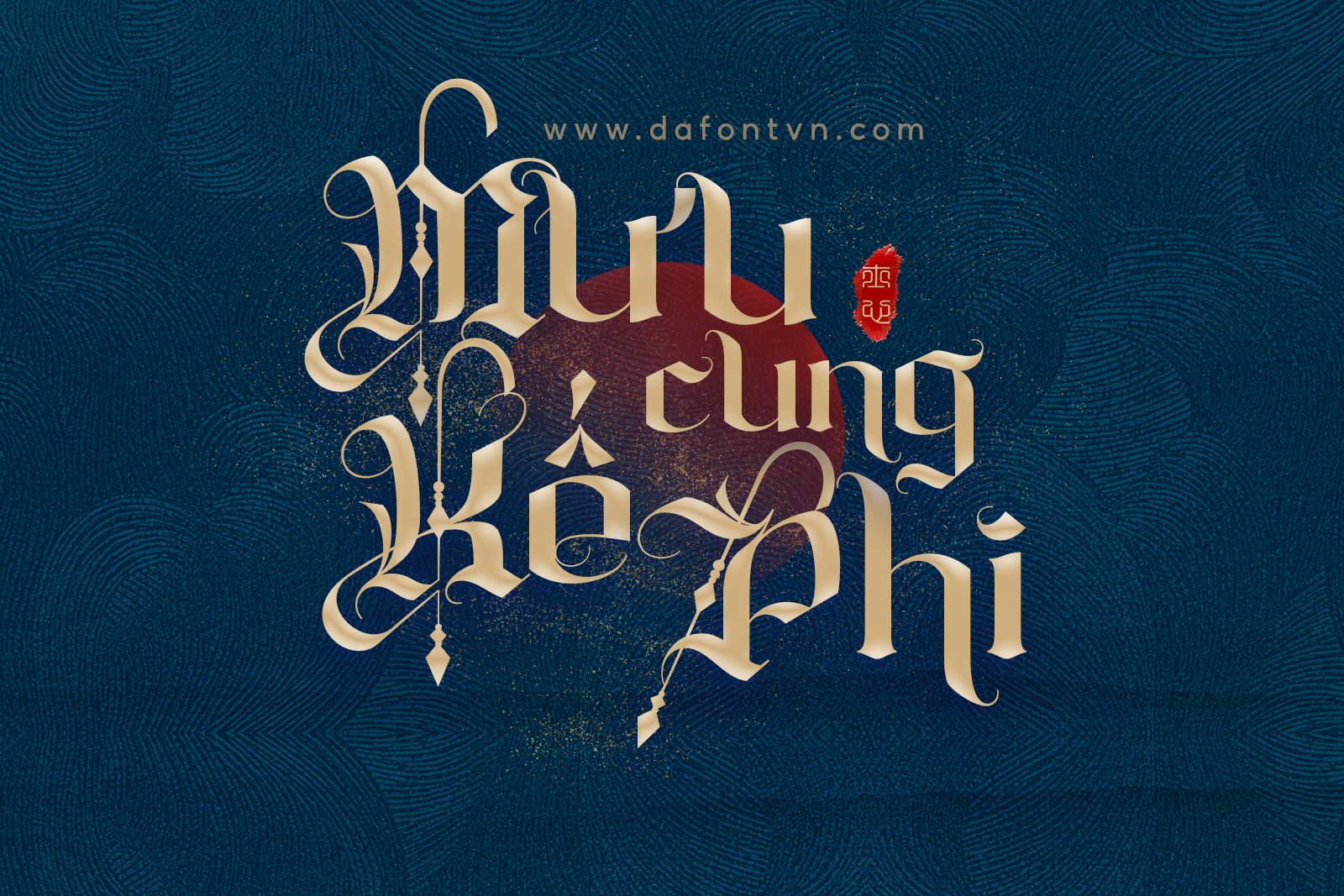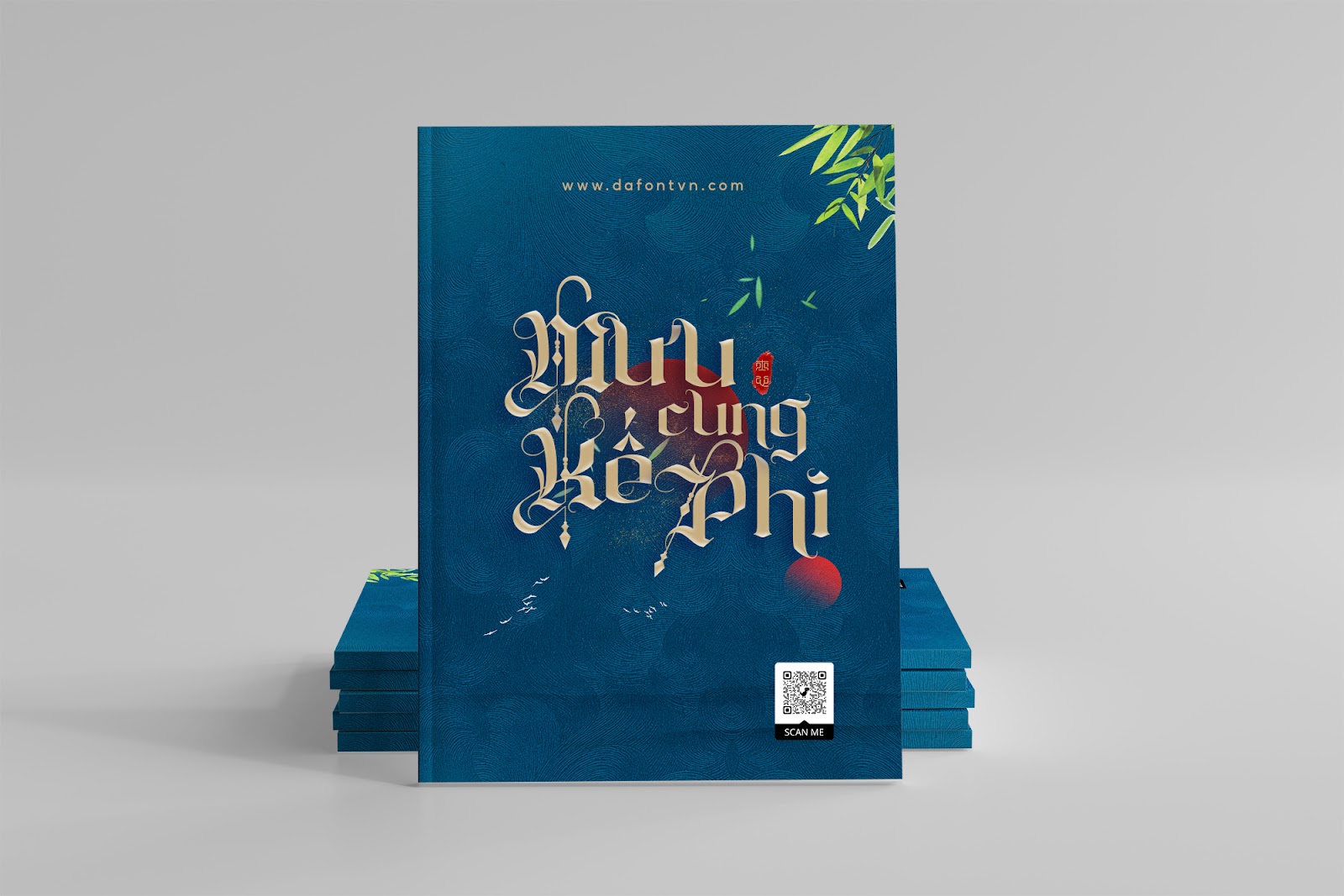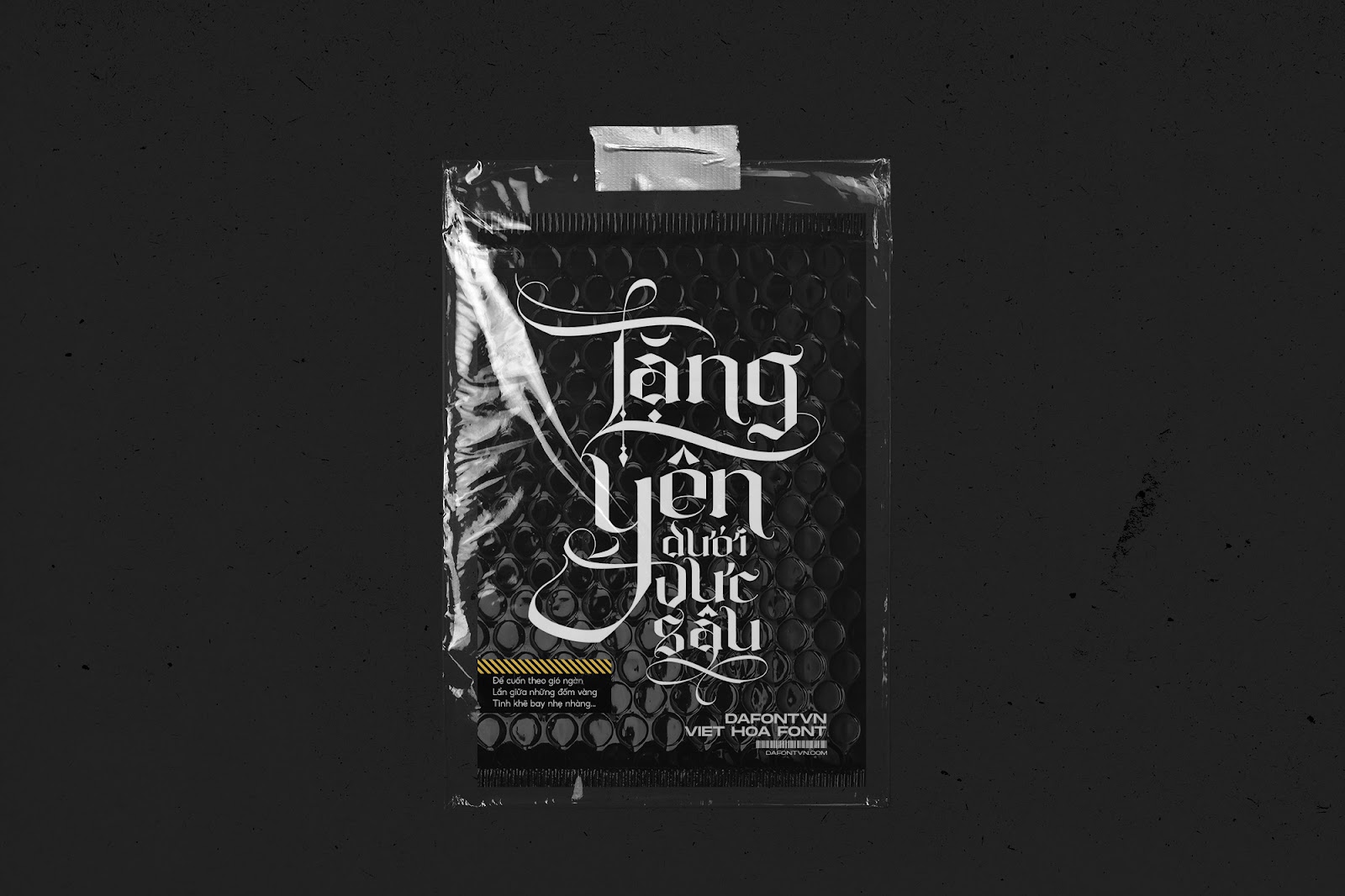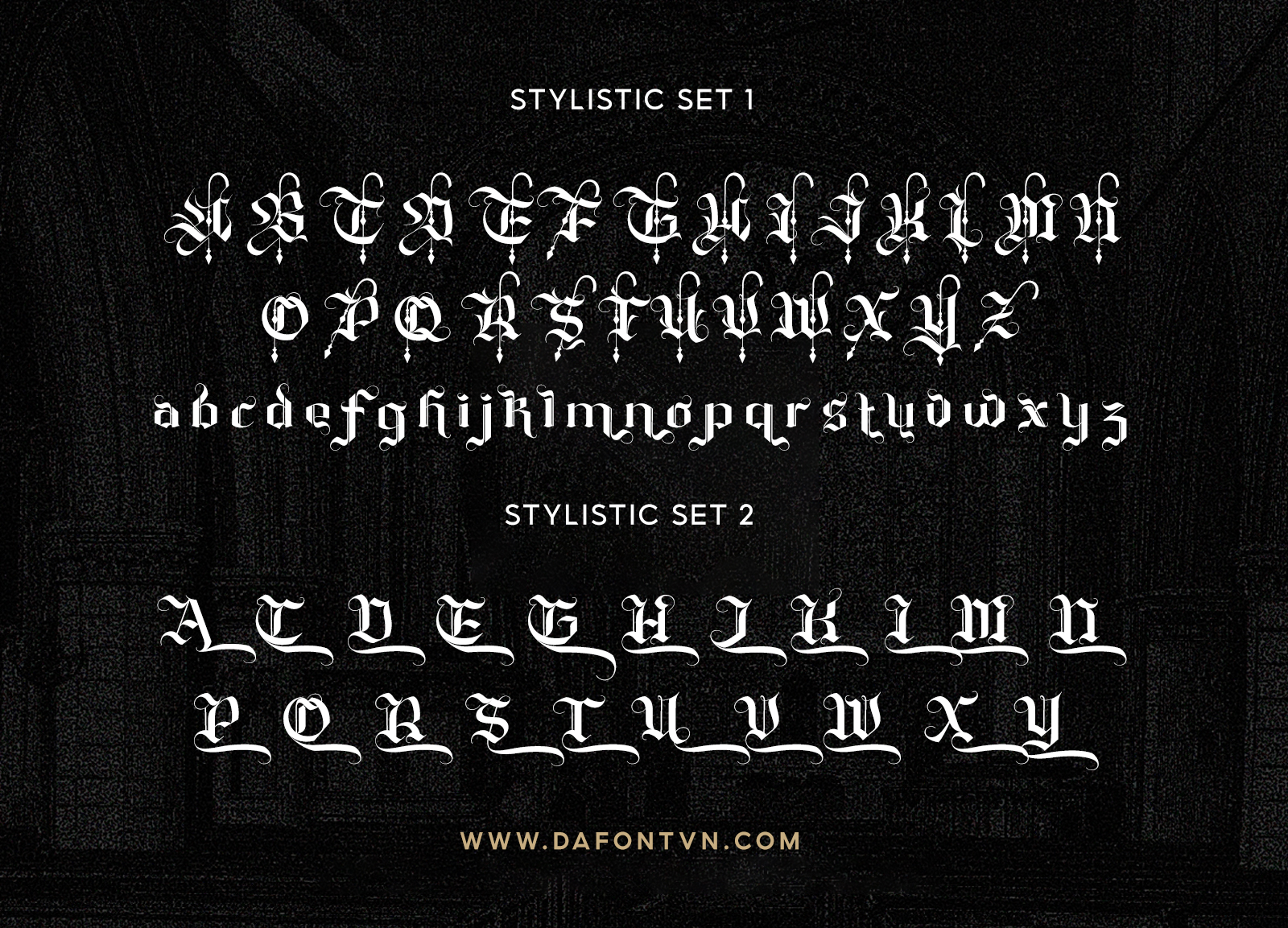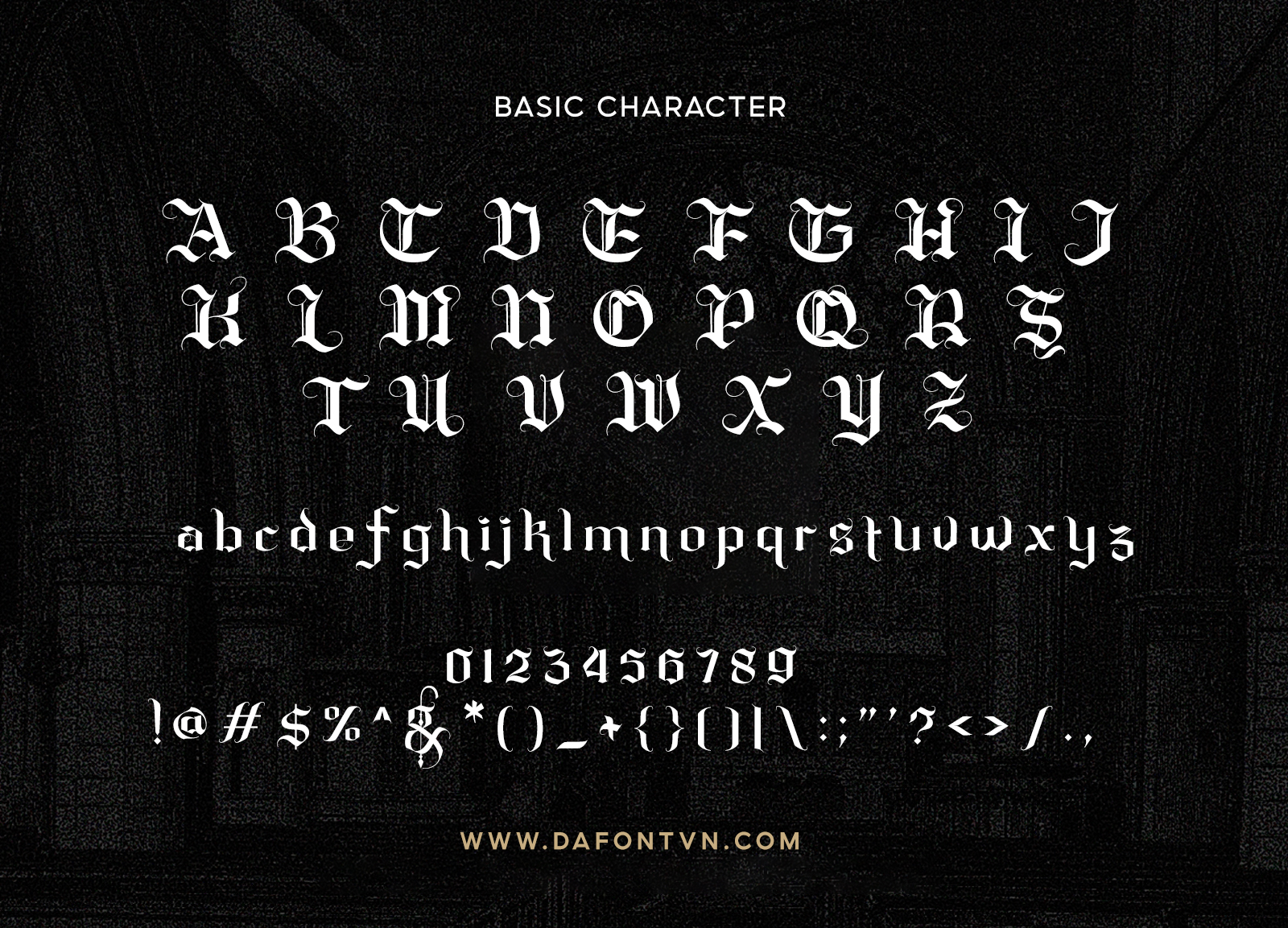
Font Ghelisyah Việt hóa – Phù hợp thiết kế cổ trang
Ghelisyah là một phông chữ lấy cảm hứng từ kiểu chữ Blackletter với phong cách hiện đại và độc đáo khá phù hợp dành cho việc thiết kế cổ trang. Đặc biệt các tùy chọn thay thế như swash, chữ ghép và các ký tự thay thế cực đẹp làm cho font Ghelisyah mang dấu ấn đặc trưng và dễ kết hợp để tạo ra những thiết kế ấn tượng hơn.
Font Ghelisyah việt hóa rất phù hợp để thiết kế cổ trang, bìa truyện, hình xăm, bao bì, logo, các thiết kế cần sự mạnh mẽ và mang phong cách Gothic hoặc bất kỳ thiết kế nào cần sự phá cách độc đáo.
Font Ghelisyah Việt hóa
Font việt hóa Ghelisyah
Ghelisyah Font - Font cổ trang việt hóa
Font Ghelisyah - Stylistic
Font Ghelisyah - All Character